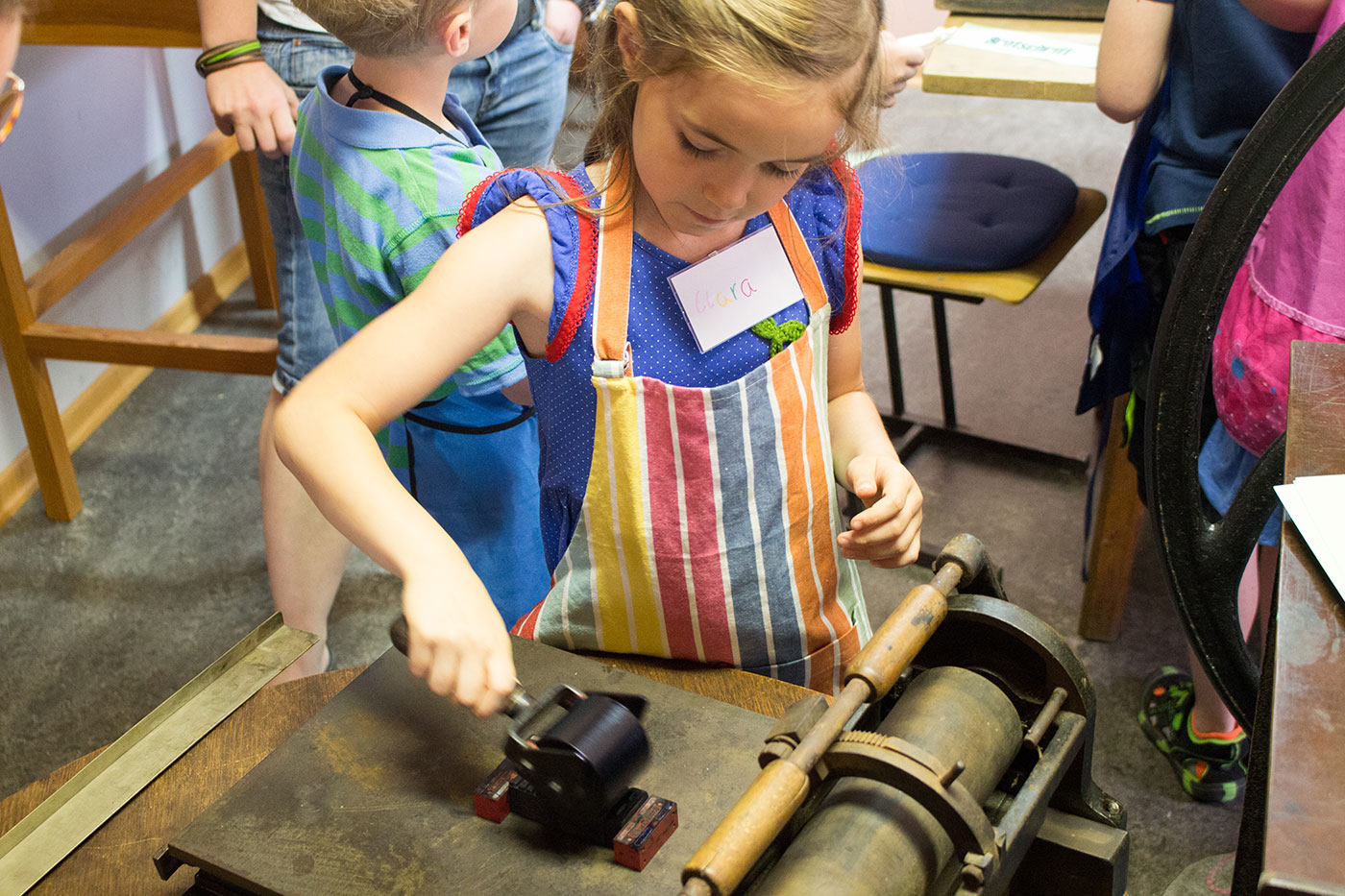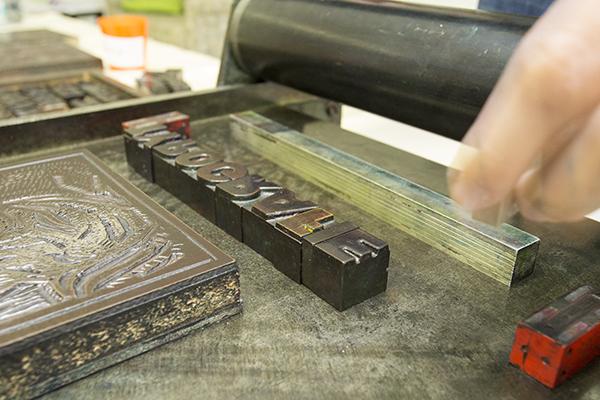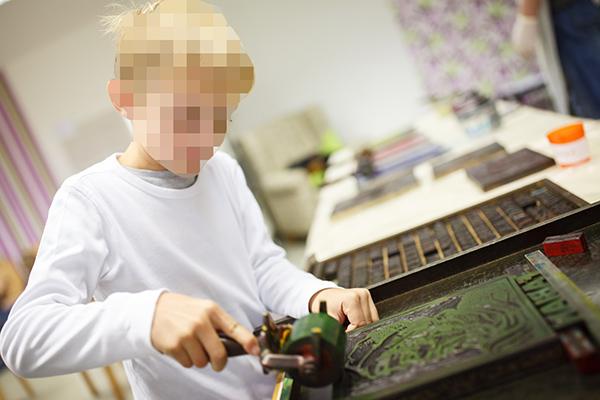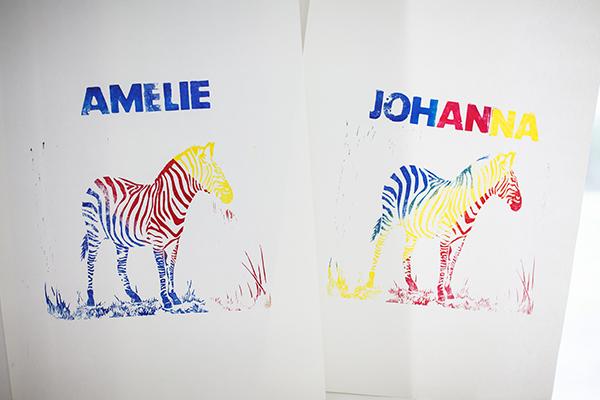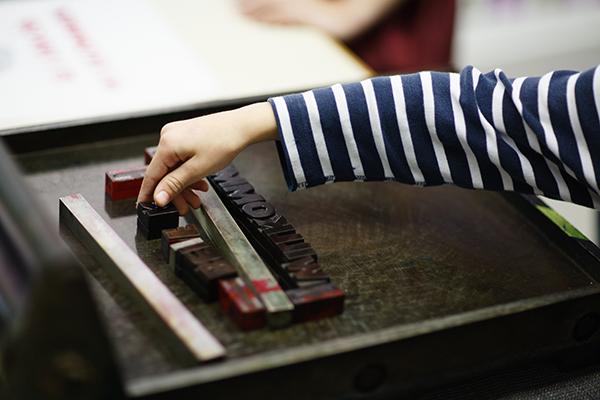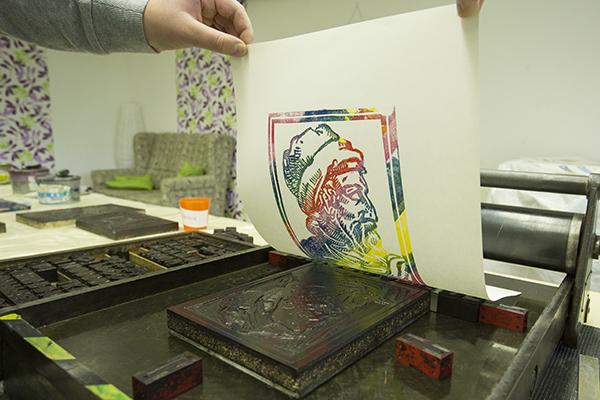
Kinder drucken mit Lettern
Vor einiger Zeit hatte ich im Forum gefragt, wie man mit Kindern möglichst einfach mit Lettern drucken kann. Die Diskussion wanderte damals sehr streitbar in eine völlig andere Richtung ab, deshalb erlaube ich mir heute die Ergebniss in einem neuen Thema vorzustellen.
Meine Aufgabe: Kinder sollen das Prinzip "Drucken mit beweglichen Lettern" verstehen. Hintergrund war die Geschichte Luthers, der Bibelüberstzung und des Druckes durch Gutenberg.
Das Problem: Ich konnte keine Holzlettern mehr auftreiben und somit keine machbar DIY-Druckerei basteln. Anregungen hatte ich aus dem Forum reichlich bekommen, vielen Dank dafür. Blei wollte ich die Kindern aber nicht anfassen lassen und die Schriften waren mir für Kinderhände zu klein.
Die Lösung: Die Druckwerkstatt des Gutenberg-Museums in Mainz verleiht eine mobile Druckwerkstatt, die ganz genau das kann, was ich gesucht hatte. Kosten 100 Euro für ein Wochenende plus 50 Euro Kaution. Sehr nette Menschen geben dort eine Einführung. Es gab einen Setzkasten mit etwa 5 cm großen Holzbuchstaben und ich durfte mir 4 fertige Druckmotive aussuchen. Von Lappen, Reinigungsbenzin, Farbe, Spachtel bis zu den Farbrollen ist alles in einer Kiste dabei. Die Handpresse hat ein ordentliches Gewicht und lässt sich nur mit zwei Leuten ins Auto heben.
Das Ergebnis: Den Kindern im Workshop (Gruppe mit 14 Kids) hat es sehr viel Spaß gemacht. Wir haben zunächst Fehldrucke zugelassen, damit das mit dem richtigen Setzen auch verstanden wird. Die Kids waren total begeistert von der Intensität der Farben auf dem Blech und der Rolle. Wir durften  die Farben übereinander rollen (streng mit gelb beginnend) und konnten so kunterbunte Drucke erzeugen. Auch das Mischen der farben konnte so verstanden werden. Den Betreuern und mir hat das aber noch mehr Spaß gemacht und wir haben in der Mittagspause für alle 70 Kinder dieses Tages  ein einfaches Plakat mit dem Tagesmotto produziert.
Ein Punkt war leider nicht zu finden im Setzkasten. Den habe ich dann nachgemalt. Aber: (ganz ehrlich) ich hatte TYPOGRAFIE.DE statt .INFO gesetzt, peinlich, dehalb zeige ich das Ergebnis nicht.
Ein buntes Abbild vom Herrn Gensfleisch.